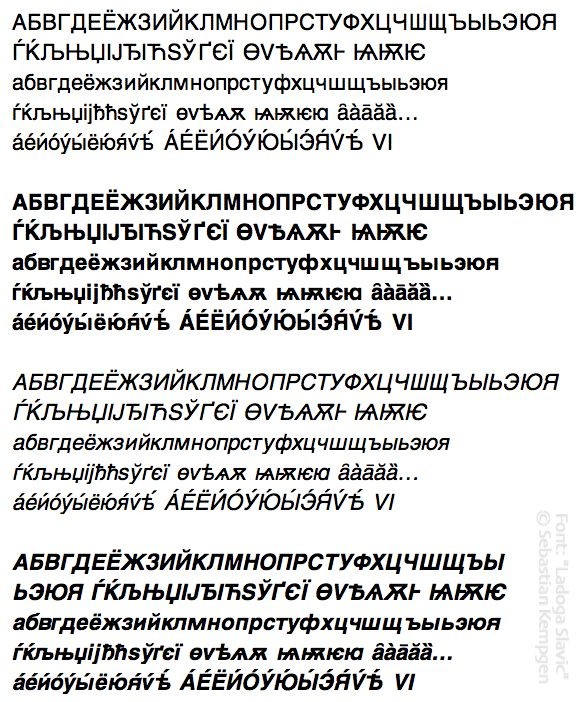
Ladoga Slavic -- ein klassischer kyrillischer Zeichensatz in der wissenschaftlichen Codierung von MacCampus. Geläufige Varianten: Ladoga Russian (wissenschaftliche Codierung, nur Russisch), Bonus: Ladoga ApSlav (Mac-Standard-Codierung).
Schnitte: regular, bold, oblique, boldoblique
Besonderheiten: Moderne Orthographie sowie ältere Orthographie, perfekt akzentuierte Vokale, auch ältere